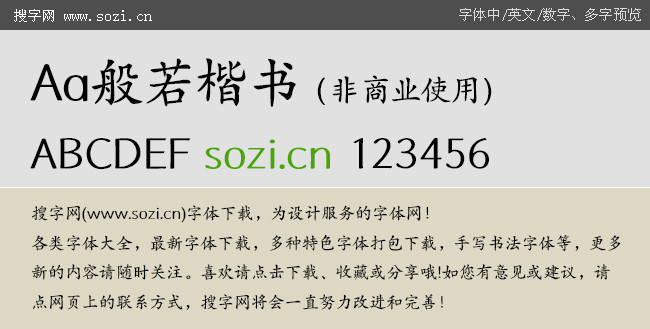
Aa般若楷書
搜字網(wǎng)給大家提供一款A(yù)a般若楷書(非商業(yè)使用)中文字體下載,該字體是一款中文楷體字體,字體筆觸較為粗實(shí),簡(jiǎn)潔大方,字形端正大氣。適合書裝設(shè)計(jì)、包裝設(shè)計(jì)、海報(bào)設(shè)計(jì)等應(yīng)用(此字體為個(gè)人非商用版,商用可以聯(lián)系QQ:1006760504)。